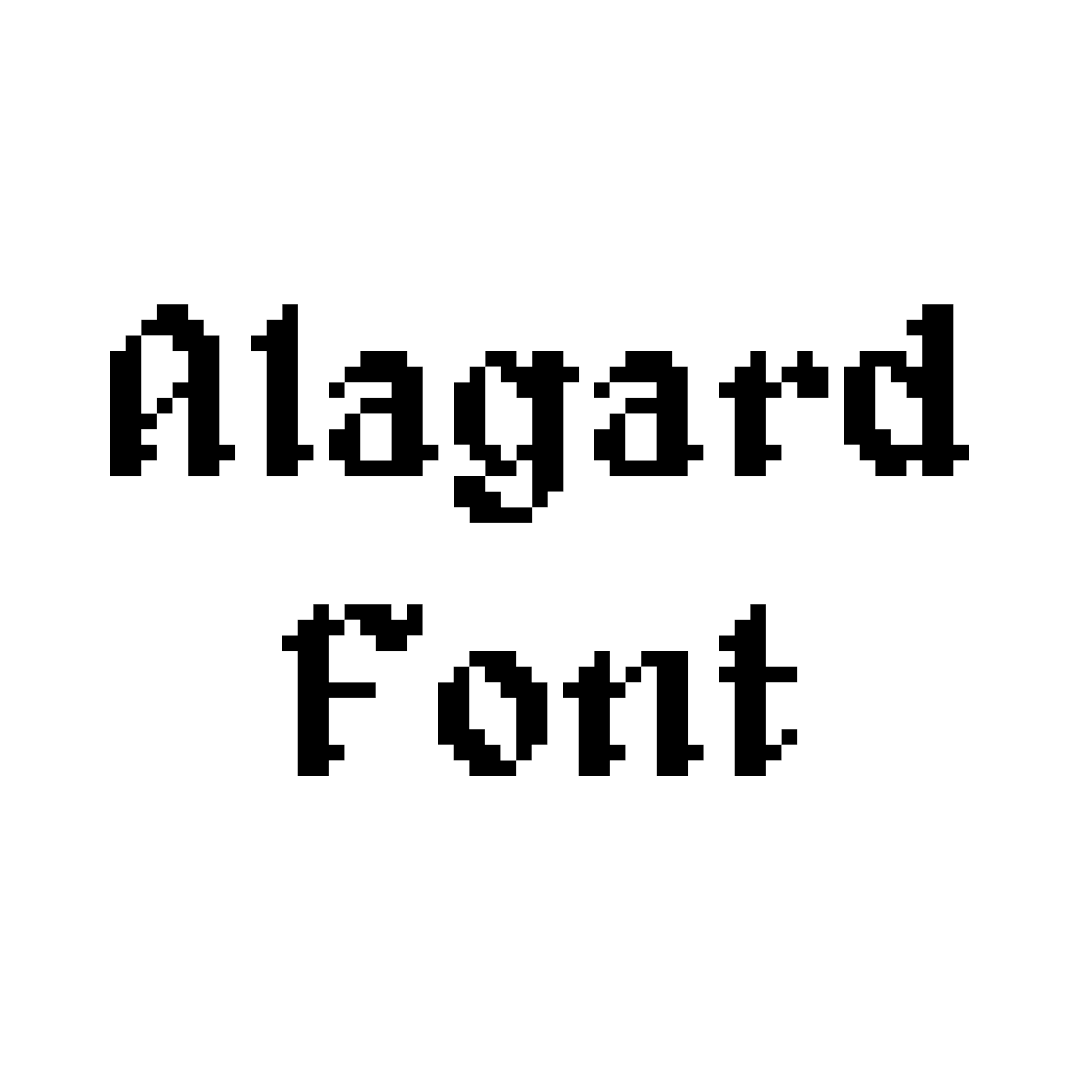
Don't You Think Minecraft's Font is a Bit Boring? Попробуйте этот текстовый пакет!
Если вы давно играете в Minecraft, то наверняка заметили, что стандартный шрифт в игре довольно простой и однообразный. Но что, если мы скажем вам, что можно легко изменить его, добавив уникальный стиль в ваш игровой опыт? В этой статье мы расскажем о Alagard Font — текстовом пакете, который преобразит интерфейс Minecraft, сделав его более атмосферным и стильным.
🔍 Почему стоит изменить шрифт в Minecraft?
Стандартный шрифт Minecraft — Minecraftia — отлично подходит для новичков, но со временем может показаться слишком простым. Замена шрифта позволяет:
- Добавить индивидуальности — ваш интерфейс будет выглядеть уникально.
- Улучшить читаемость — некоторые шрифты лучше подходят для длинных текстов.
- Создать атмосферу — например, средневековый или фэнтезийный стиль.
Пакет Alagard Font предлагает именно такой вариант — он добавляет в игру готический шрифт, который отлично сочетается с RPG-серверами и приключенческими картами.
🎨 Обзор Alagard Font
✨ Особенности:
✔ Готический стиль — буквы выглядят так, будто они из средневекового манускрипта.
✔ Полная замена шрифта — изменяются все тексты в игре, включая меню, чат и книги.
✔ Оптимизированная читаемость — несмотря на стилизацию, текст остается четким.
🎮 Заключение: Сделайте Minecraft еще интереснее!
Изменение шрифта — это маленькая, но важная деталь, которая может полностью преобразить ваше восприятие игры. Alagard Font — отличный выбор для тех, кто хочет добавить в Minecraft нотку средневековья или просто разнообразить интерфейс.